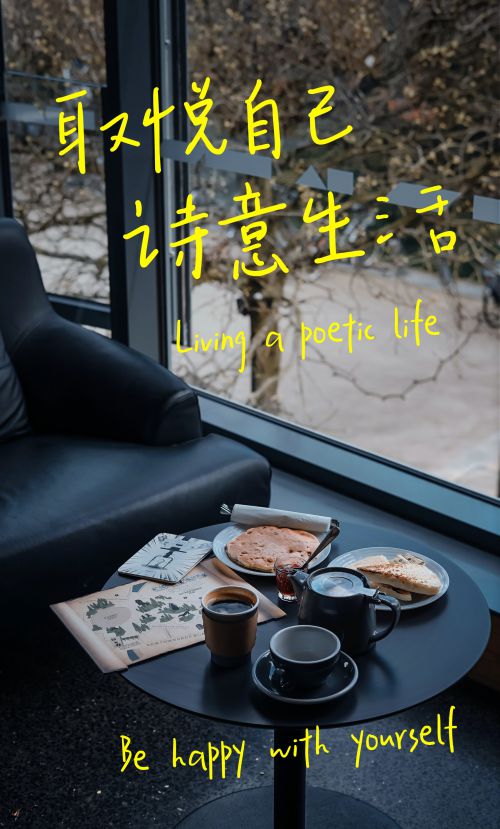
汉仪新蒂浪花体
一款清新洒落的创意手写字体。这款字体笔画纤细有力,笔画向四周伸展,富有张力。结构较为洒落,内部结构向两侧延伸,内部白空间清澈透亮,造型疏秀,给人一种浪花般的清爽感。纤细的笔画线条带有细微的粗细变化,以展现出手写的力度变化;笔画行笔流畅、转折顺滑,有着手写带来的自然弧度,略带抖动,富有手写韵味。排版后,版面效果如踏入海水中,用手轻撩海水泛出点点浪花一样,清新爽快、富有节奏感。该字体适合作为标题字与短文案用字,用在图书、海报、广告、影视等需要表现手写感、清新感、休闲感的场合。